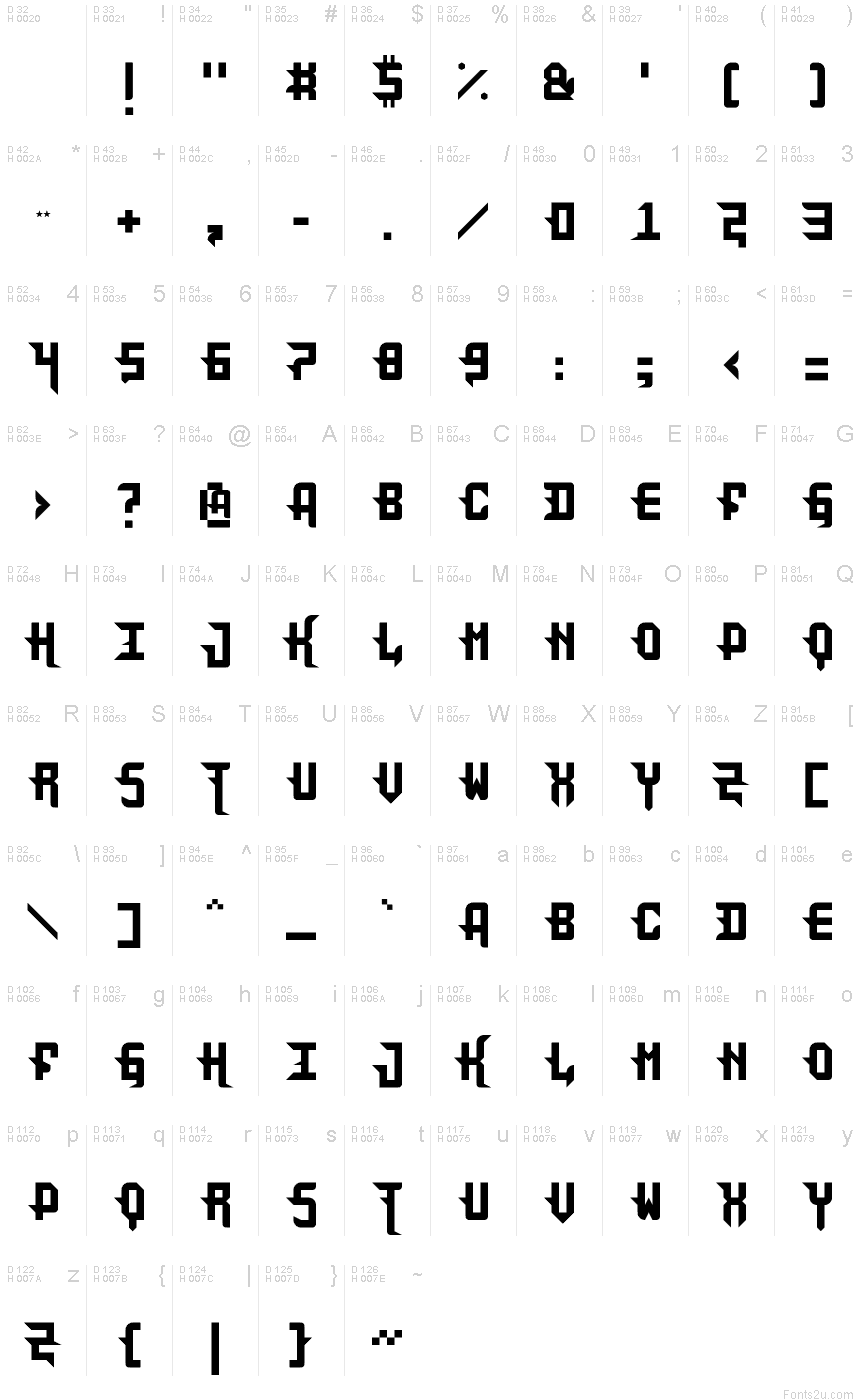
DarkPix Gothic 由 Juan Casco 设计,是一款免费的几何黑体(Blackletter)字体,它将哥特式大写字母重塑为坚硬的块状结构。宽笔画、切角处理以及深邃的三角形切口赋予了字母一种严谨的建筑韵律,而几处弧线转折又避免了过于机械化的观感。
它非常适合用于金属乐和工业风专辑封面、游戏 Logo、活动海报、街头服饰设计以及恐怖题材标题。作为一款免费字体,它在短标题或紧凑的文字标识中表现最佳,密集的轮廓与刀锋般的刻痕能充分展现其独特氛围。